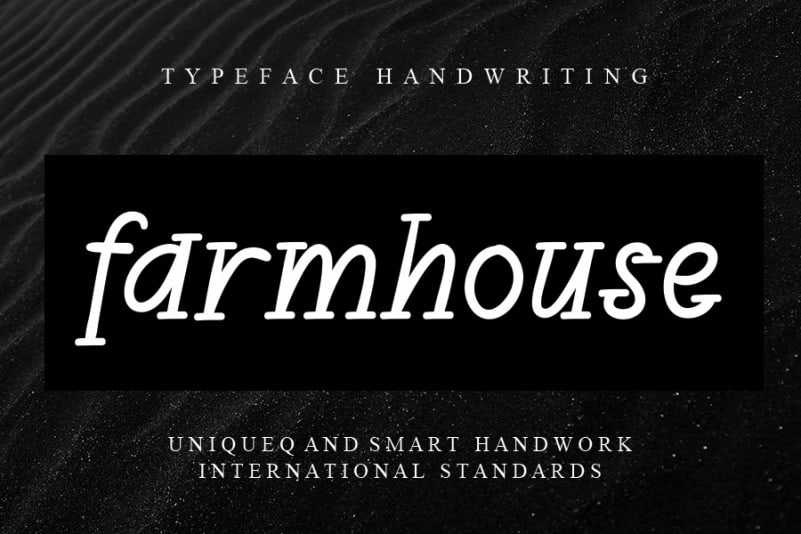
Farmhouse Display Font – Download Grátis
A Farmhouse Display Font é uma seleção única para aqueles que buscam uma paixão vintage e autêntica no seu design. Esta fonte foi criada com toques leves de originalidade, projetando-se como um complemento perfeito para trabalhos inspirados na arquitetura rústica dos anos 70 e 80. Com linhas curvas delicadas e traços que destacam sua simplicidade, ela adiciona uma sensação de genuinidade e alegria às criações digitais. Seja em logotipos, letras capitais ou headlines, esta fonte transforma qualquer projeto em algo único, chamando atenção e deixando um impacto duradouro. A Farmhouse Display Font é perfeita para designers que buscam trazer uma atmosfera de simplicidade e leveza ao seu trabalho. Se você está procurando por uma fonte exuberante que não só faz sua marca mais memorável, mas também adiciona a essência do estilo rústico à sua criação, essa é a escolha certa.